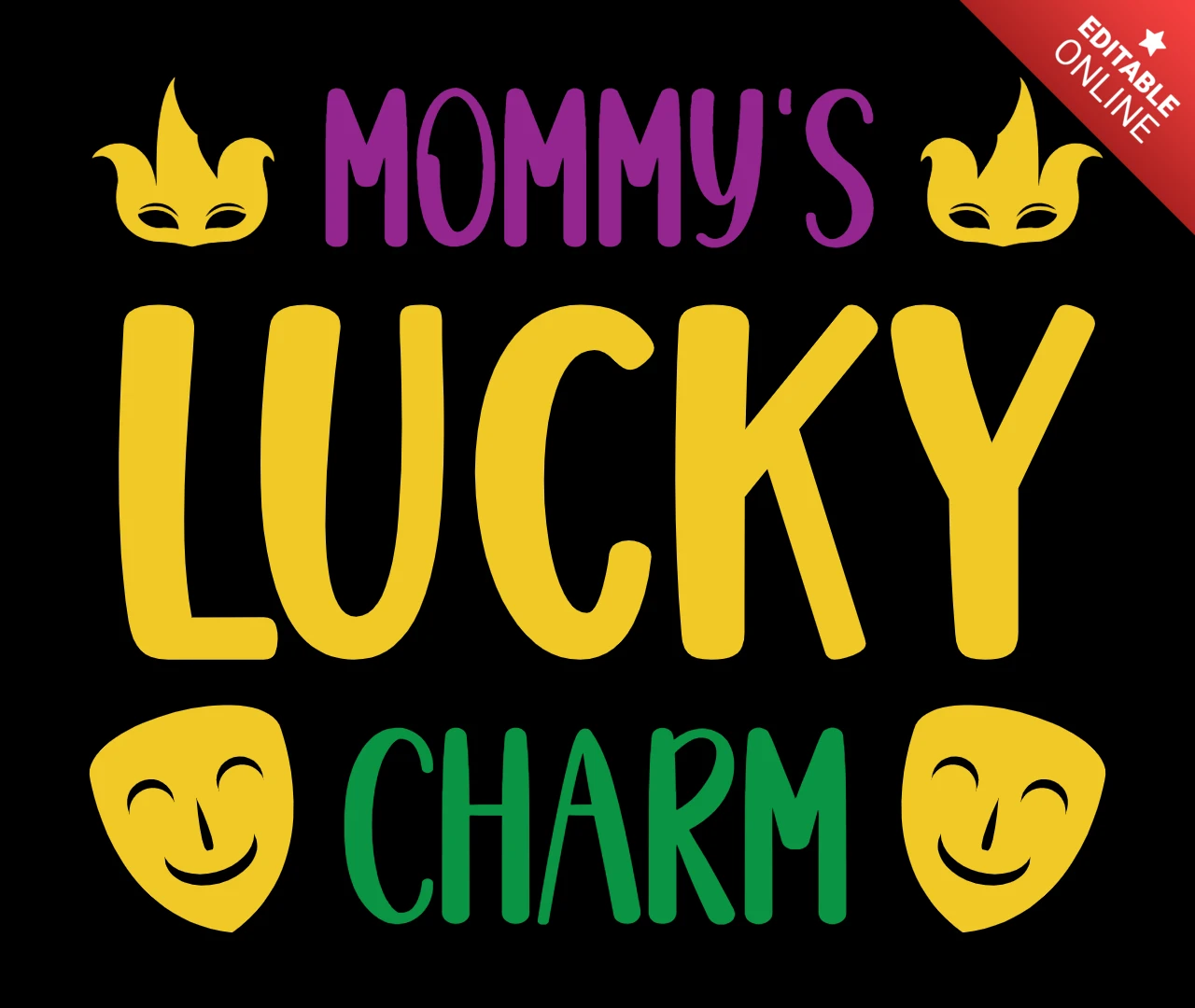
Le porte-bonheur de la maman : modèle de design festif avec typographie ludique
Éditer dans Design Studio Télécharger en JPGRehaussez votre célébration du carnaval avec notre modèle de conception coloré, doté d'une typographie ludique et de masques joyeux - parfait pour les vêtements, les affiches, les autocollants et le merchandising familial de ce mardi gras !